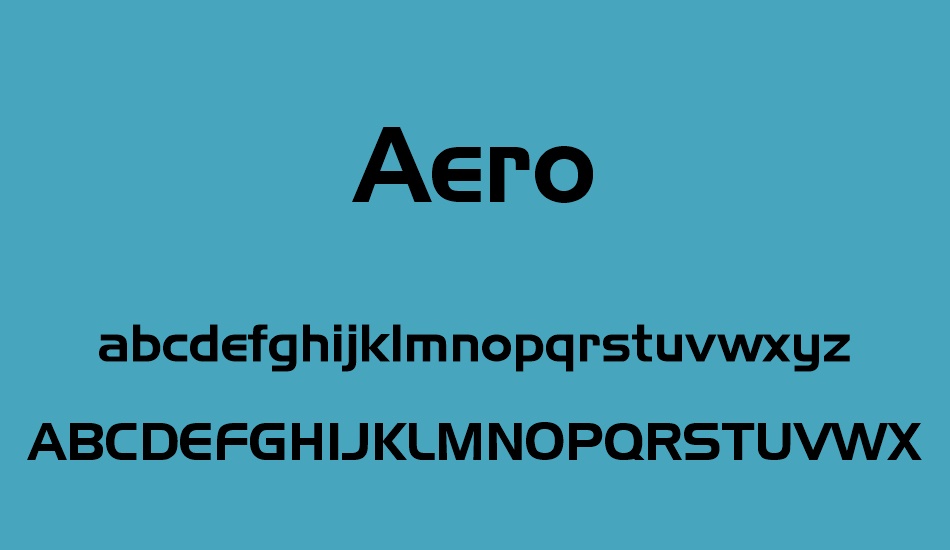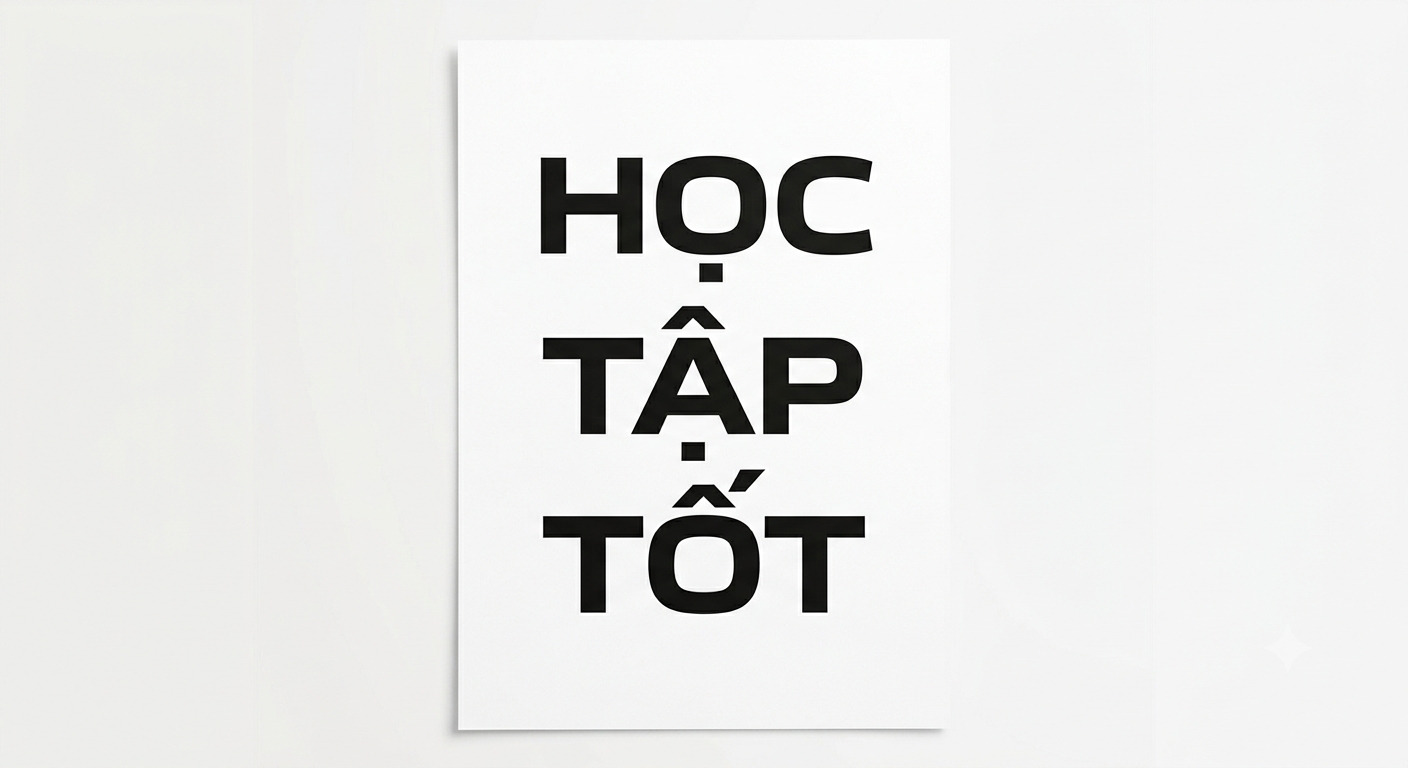
Font Aero là gì?
Aero là một bộ phông chữ thuộc dòng Sans-serif hiện đại, gây ấn tượng bởi cấu trúc chữ rộng, các đường nét bo cong mềm mại nhưng vẫn giữ được sự vững chãi. Phông chữ này mang hơi thở của sự chuyển động, tốc độ và tính kỹ thuật cao, thường gợi nhắc đến ngành hàng không hoặc công nghệ tương lai. Đây là sự lựa chọn phù hợp cho các thiết kế logo công ty vận tải, bao bì thiết bị điện tử, tiêu đề website công nghệ hoặc các ấn phẩm truyền thông yêu cầu sự năng động, bứt phá.
Trong đó, biến thể font aero bc thường được các designer ưu tiên sử dụng cho các vị trí tiêu đề chính nhờ độ dày nét vừa phải và khả năng hiển thị rõ ràng trên nhiều bề mặt vật liệu. Tuy nhiên, các bản gốc tiếng Anh thường không tương thích với bảng mã Unicode tiếng Việt, dẫn đến sai lệch vị trí dấu thanh. Bản việt hóa được Xưởng In Viva cung cấp đã xử lý kỹ lưỡng các vấn đề kỹ thuật này, đảm bảo các ký tự có dấu hiển thị hài hòa, giữ nguyên tinh thần phóng khoáng của bộ chữ gốc khi ứng dụng trên hộp quà tặng hay túi giấy cao cấp.
4 ứng dụng font Aero Việt hóa trong thiết kế và in ấn
Với phong cách chữ hiện đại, mạnh mẽ cùng cấu trúc hình học rõ ràng, font Aero Việt hóa phù hợp với nhiều thiết kế bao bì, quà tặng và sản phẩm nhận diện thương hiệu theo hướng công nghệ:
- Thiết kế bao bì linh kiện điện tử: Font Aero phù hợp để in tên sản phẩm trên hộp cứng đựng tai nghe, chuột máy tính, sạc dự phòng nhờ kiểu chữ rõ nét, tạo cảm giác chuyên nghiệp và hiện đại.
- Khắc laser quà tặng công nghệ: Logo sử dụng font Aero khi khắc trên USB, sạc dự phòng hoặc phụ kiện kim loại giúp sản phẩm có thêm điểm nhấn cá nhân hóa, phù hợp với các chương trình tặng quà doanh nghiệp.
- Sản xuất bộ quà tặng văn phòng in logo: Aero có thể ứng dụng trên bình giữ nhiệt, sổ tay da, bút ký hoặc phụ kiện văn phòng bằng kỹ thuật in UV, tạo sự đồng bộ cho bộ nhận diện thương hiệu.
- Trang trí backdrop và banner sự kiện: Với định dạng vector, font Aero có thể sử dụng cho tiêu đề chương trình, khu vực check-in hoặc gian hàng triển lãm mà vẫn giữ được đường nét rõ ràng khi phóng lớn.
5 lưu ý khi sử dụng font Aero Việt hóa trong sản xuất
Để font Aero Việt hóa giữ được độ sắc nét khi đưa vào sản xuất thực tế, designer cần chú ý:
- Kiểm soát khoảng cách ký tự (Tracking): Aero có cấu trúc chữ khá rộng. Khi in trên các bề mặt cong như bình giữ nhiệt hoặc ly sứ, nên điều chỉnh khoảng cách giữa các ký tự để bố cục logo dễ nhìn hơn.
- Tối ưu đường Path khi gia công bế nổi: Chuyển đổi font Aero sang dạng vector và xử lý các điểm neo giúp đường nét chữ ổn định hơn khi thực hiện dập nổi logo trên hộp giấy hoặc bao bì cao cấp.
- Kiểm tra độ dày nét khi in: Với các phương pháp in trên vải canvas, kim loại hoặc nhựa, cần kiểm tra khoảng trống bên trong ký tự để hạn chế tình trạng mực bị dồn gây mất chi tiết.
- Thiết lập hệ màu CMYK phù hợp: Các thiết kế dùng Aero thường kết hợp với màu bạc, xám, đen hoặc xanh công nghệ. Cần kiểm tra thông số màu trước khi in để thành phẩm có sự đồng nhất với bản thiết kế.
- Ưu tiên định dạng Vector khi in kích thước lớn: Khi sử dụng font Aero cho banner, pano hoặc backdrop, file vector giúp hạn chế tình trạng giảm chất lượng khi phóng lớn.